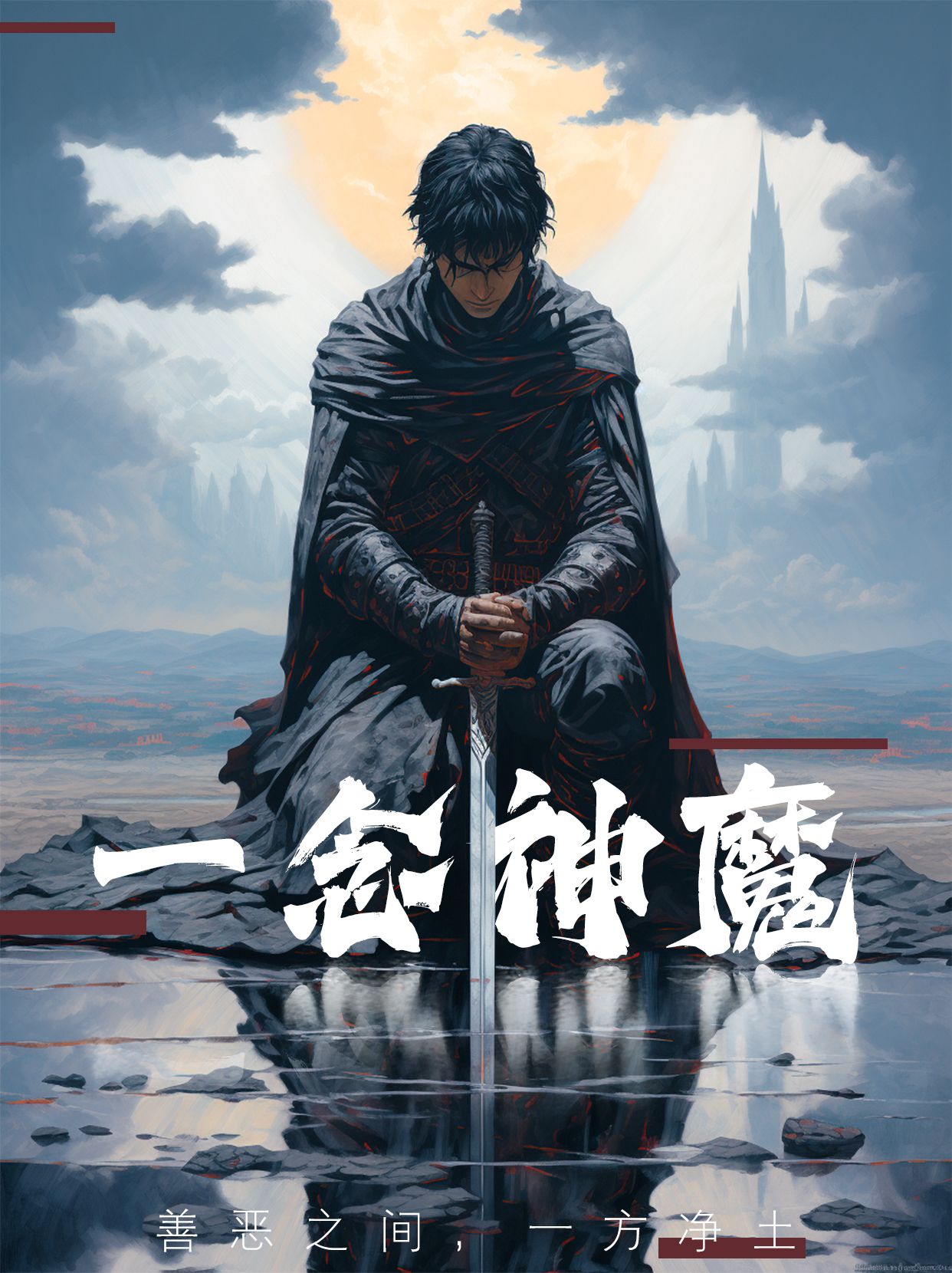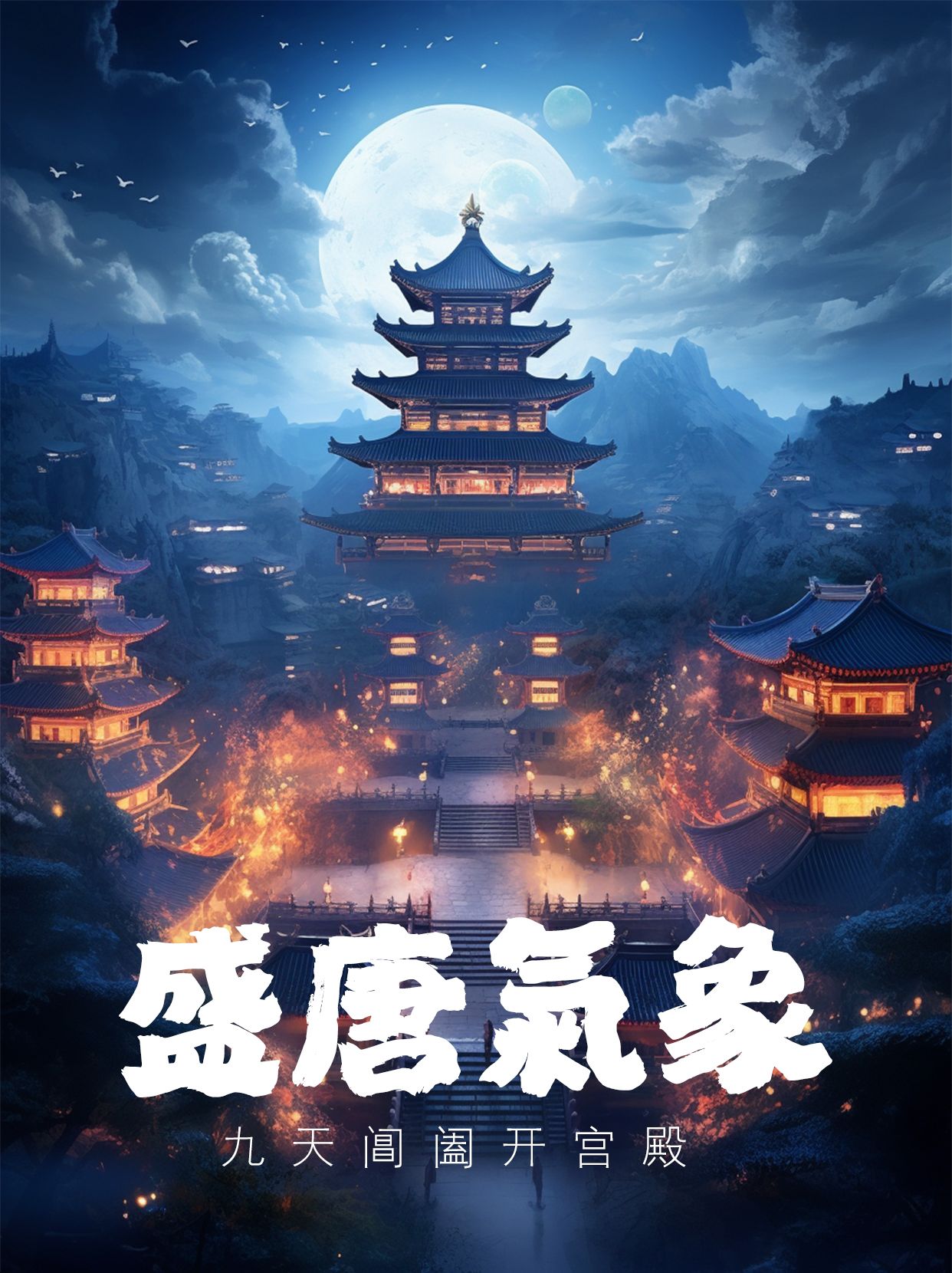
《封神》票房逆袭,2023年奇幻神话电影宣传都用什么字体?
火透整个夏天的电影当属《封神第一部:朝歌风云》,无论是恢弘巨制的电影特效、奇幻磅礴的神话色彩,还是光鲜夺目的青春肉体,都在2023年的暑期档,火遍了全国。
《封神》演员配置与人物契合度很高,在宣发方面的海报字体选择的也特别有时代背景,励字造梦共创字库给大家精选了2款国潮书法字体,在海报设计中特别亮眼。
笔墨浓厚,粗细对比较为明显,字体结构较为中正,字体里笔画的“勾、提、挑、捺”等笔画特点明显、夸张,极具视觉冲击力,单字结构收放自如。
字体中正感官丰富,运笔富有节奏感,呈一波三折之态,笔画粗细变化明显,略有飞白,转折方圆相结合。